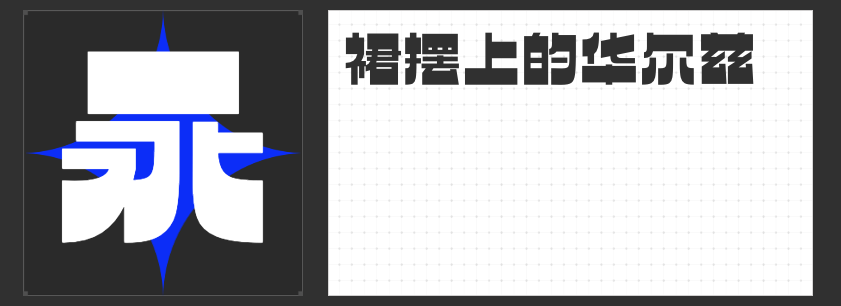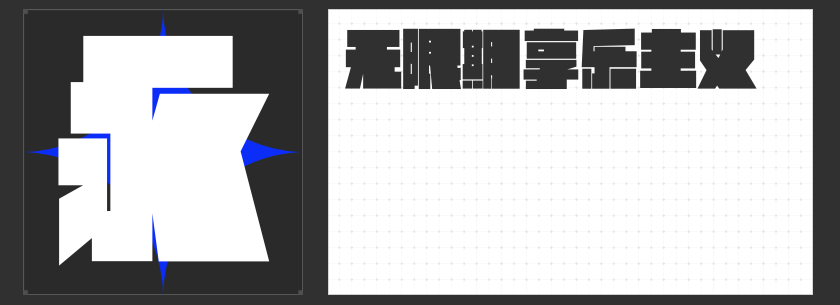
逆反差字体新风尚:探索“励字”系列的独特魅力
在字体设计的浩瀚宇宙中,逆反差字体以其独特的视觉冲击力与表现力,成为了设计界的一股清流。今天,就让我们一同走进“励字”系列,领略其中两款备受瞩目的逆反差字体独特魅力。
这款字体以其方正而不失灵动的字型设计,完美融合了软硬兼备的特质。笔画间的粗细对比鲜明,尤其是在撇、捺、钩及部分点笔画上,采用了饱满的弧线处理,赋予了字体一种优雅的圆弧美感。中宫较大的设计使得文字整体看起来更加稳重,重心平稳,笔画对称,无论是阅读还是展示,都能带来极佳的视觉享受。
如果说“励字逆反差圆舞简 超级黑”是优雅与力量的结合,那么“励字宽边黑简 超级黑”则是对传统字体风格的一次大胆突破。它打破了常规的平衡,通过右部加粗、左部减细的巧妙设计,营造出一种强烈的视觉张力,让人一眼难忘。字型规整方正,笔画横平竖直,粗细对比的极致展现,赋予了字体厚重的质感与强烈的视觉冲击力,无论是用于标题还是正文,都能迅速抓住观者的眼球。
两款字体,各具特色,共同诠释了逆反差字体的无限可能。无论是追求现代简约的设计项目,还是需要强烈视觉效果的广告宣传,它们都能成为你设计作品中的点睛之笔,让文字不仅仅是信息的载体,更是艺术与创意的展现。